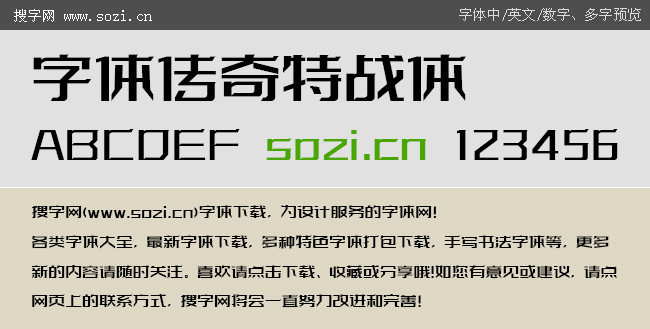
字體傳奇特戰(zhàn)體
搜字網(wǎng)給大家提供一款字體傳奇特戰(zhàn)體中文字體下載,該字體根據(jù)GB2312編碼設(shè)計,整套字庫包含6763個簡體中文漢字,整體字形設(shè)計采用橫細(xì)豎粗的設(shè)計風(fēng)格,橫線右端傾斜修飾,豎線右上角尖角修飾變形,整體視覺統(tǒng)一剛勁有力。適合包裝設(shè)計、書裝設(shè)計、海報設(shè)計等應(yīng)用,此字體可免費(fèi)商用。